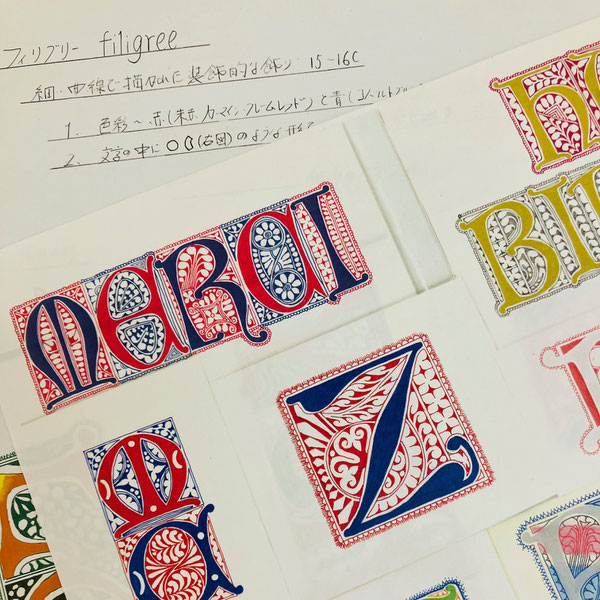
書体はやや丸みのある比較的初期のゴシック体(カロリン体から発展)や、南ヨーロッパで書かれたルタンダ体などが合います。
下の画像(T.Y先生制作)のように現代的なデザインにするのも素敵です。
単独作品でなく、そこに書体を組み合わせたり、レイアウトする場合はなんでも良いわけではありません。
それを見極めるには古典を十分学んだ上で、さらに現代的に優れた感性をお持ちでないと難しいように思います。